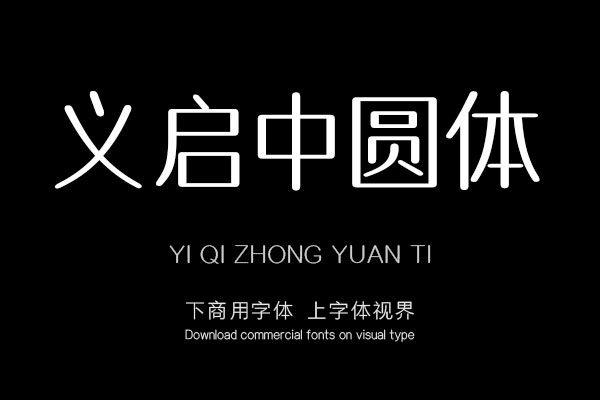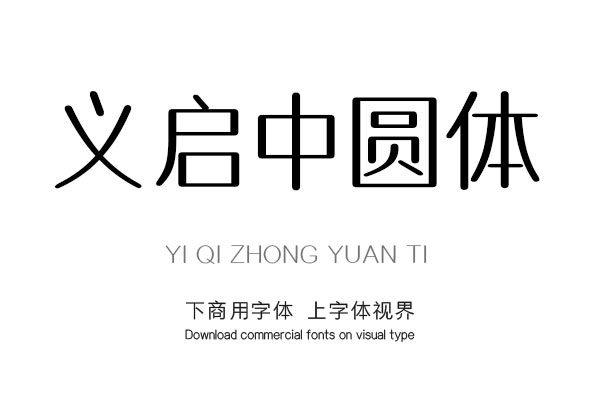
春光是生机盎然的季节,与故事一起翩翩起舞的是美丽的彩蝶。“义启字库”以“春”为设计理念,创作了“义启中圆体”这一作品。
在风的引导下,她轻轻地翻了翻腿上的书,书也淘气地翻了翻页面。春天的阳光温暖,她闭上眼睛,享受春天带来的舒适。
不远的地方,她听到了一声幼嫩的欢叫,还有大人的怪笑。"慢点,小心!孩子们一手握把,一手拉着线,昂着头往天上看,“不要摔得太重”。中年人则小跑着跟着孩子。她们身后,一个中年妇女坐在自己的桌布上,摆布着饭菜。不时有两只眼睛看着他们。
她望向天空,彩蝶的风筝在空中飞翔。小孩激动的喊叫声像一首欢歌,迎接着春天的到来。
春日是生机勃勃的季节,有些故事是如此纯洁,你知道,那是因为滋润它的是昨日的雪。
当她走的时候,全家正在快乐地野餐,脸上挂着灿烂的微笑。他的嘴角微微上翘,甚至连他自己也感觉不到。春来了,一切又重新开始。
作为创造者的观众,我们可以见证大自然一年四季的变化,感受大自然带给我们的温暖。所以才会有变化如今,对于她来说,更加努力工作,不能让这春光带给她力量。真精彩才刚刚开始,感动、心动,带着自己出发。
春来了,请你自己起程。